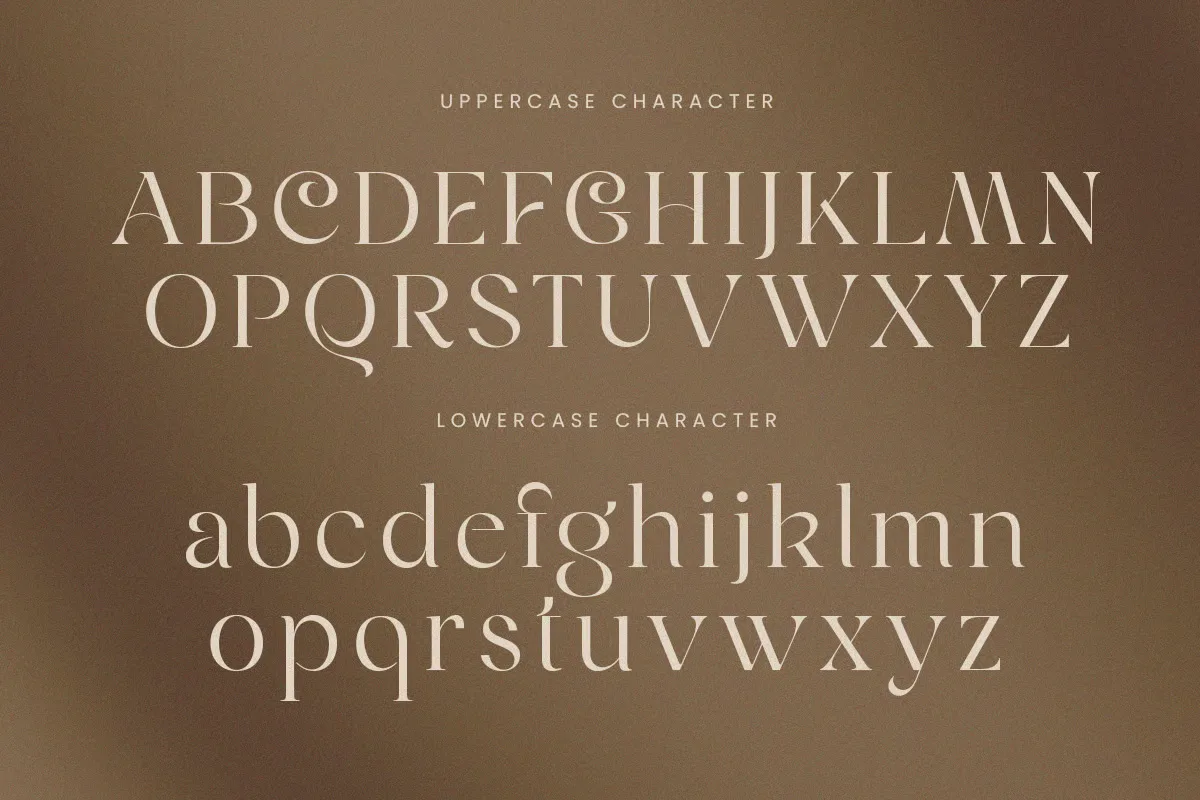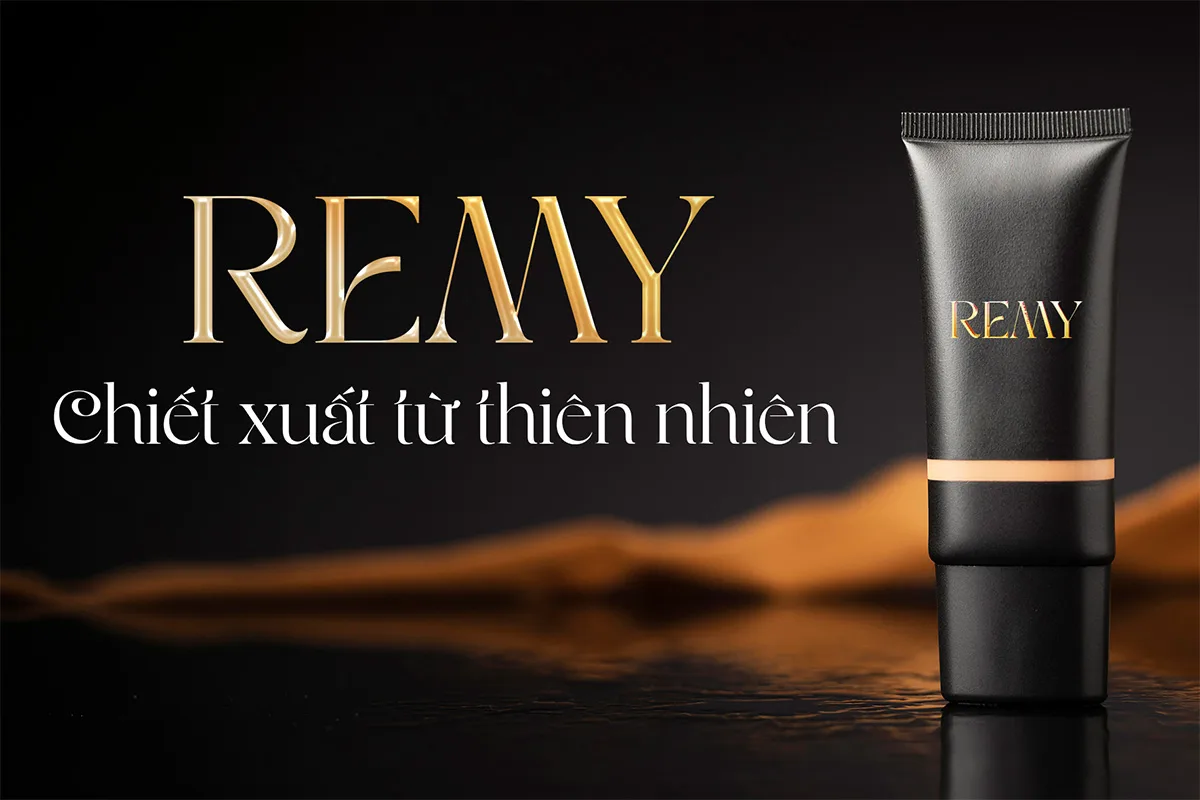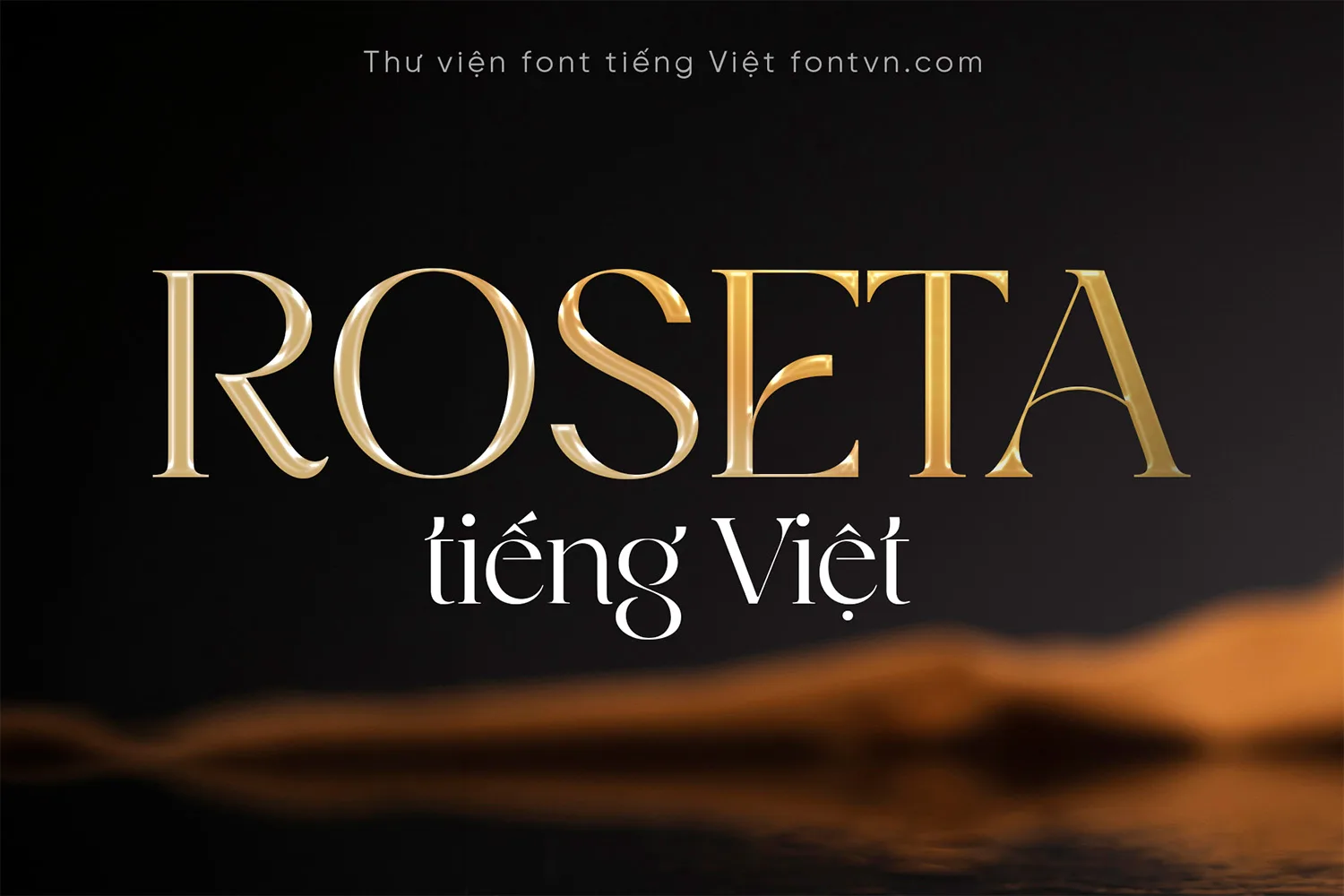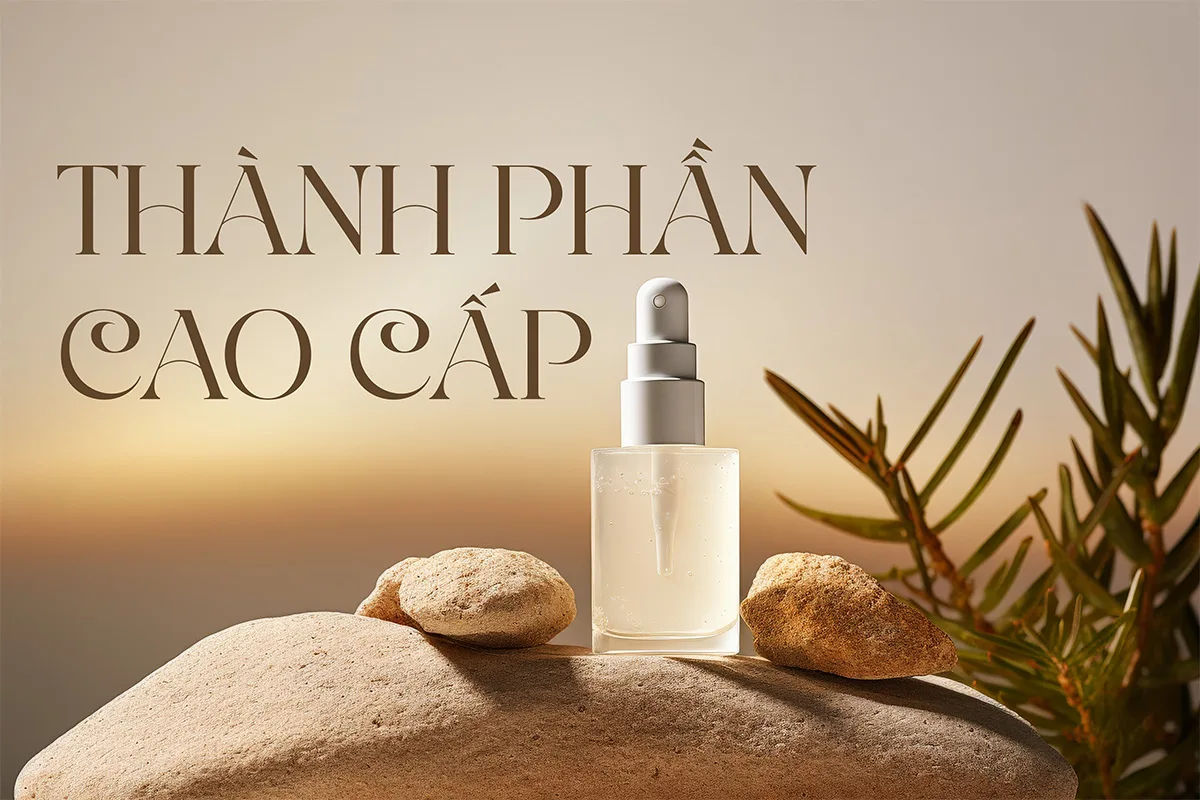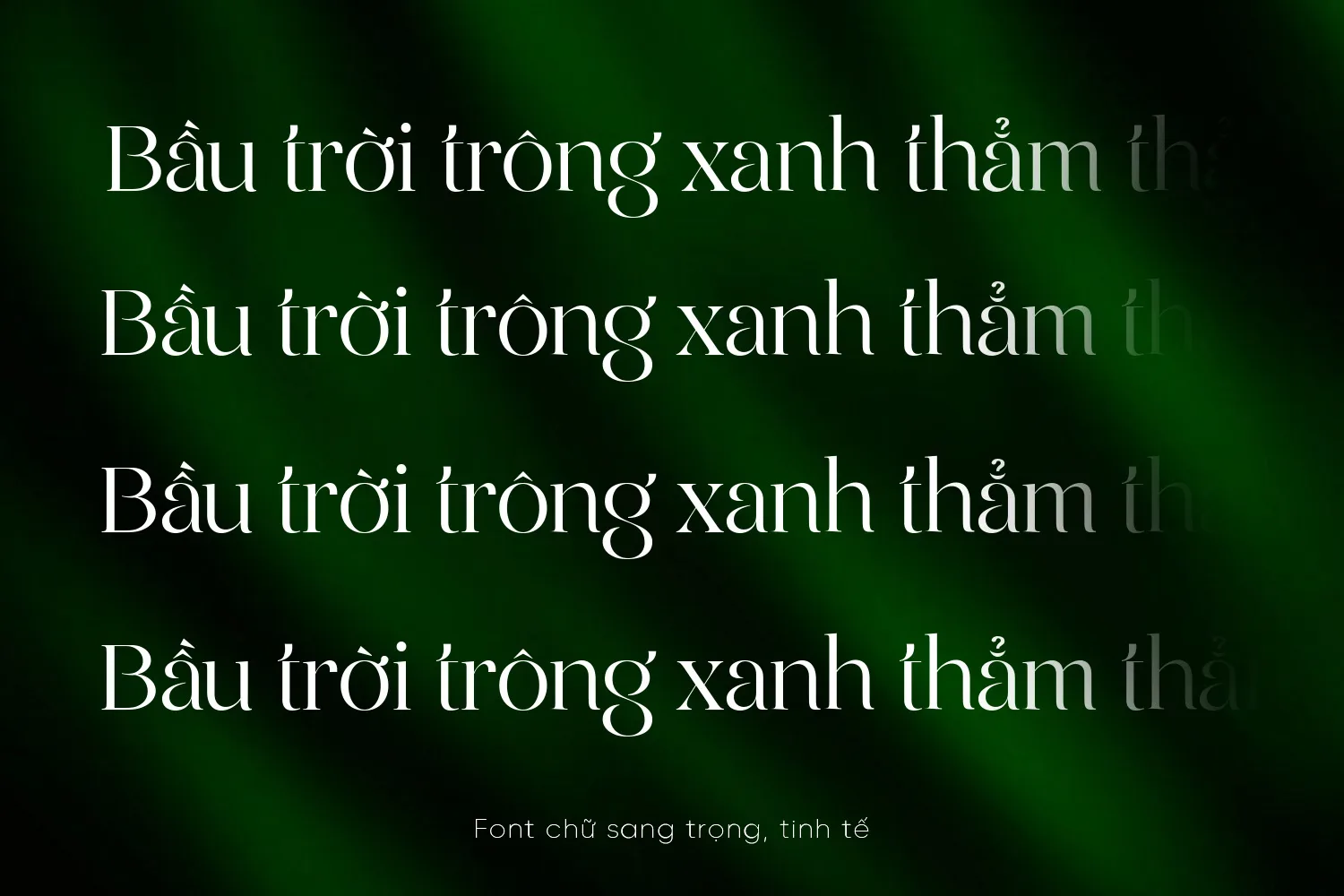
DVN Roseta tiếng Việt – Font chữ Serif Sang Trọng Và Quý Phái
DVN Roseta mang đậm ngôn ngữ thiết kế của một dòng serif cổ điển kết hợp tinh tế với hơi thở nghệ thuật đương đại. Điểm nhấn thị giác của kiểu chữ này nằm ở độ tương phản thanh đậm tinh tế, đi kèm với các chi tiết uốn lượn (swash) điệu đà được xử lý khéo léo trên những ký tự đặc thù. Sự giao thoa hài hòa giữa cấu trúc serif vững chãi và các đường cong uyển chuyển giúp tổng thể DVN Roseta không chỉ toát lên vẻ đẹp quyến rũ, thanh lịch mà còn giữ được sự sắc sảo, quý phái trong từng nét chữ.
Với diện mạo mang đậm tính nghệ thuật và sự sang trọng, DVN Roseta là giải pháp định hình phong cách hoàn hảo cho các ấn phẩm đòi hỏi tính thẩm mỹ cao. Kiểu chữ này đặc biệt phát huy thế mạnh khi được ứng dụng vào thiết kế nhận diện thương hiệu cao cấp, tiêu đề tạp chí thời trang, thiết kế bao bì mỹ phẩm xa xỉ hay những bộ thiệp cưới mang phong cách lãng mạn. Dù xuất hiện ở các không gian thiết kế tối giản hay phức tạp, DVN Roseta đều tạo ra sức hút thị giác mạnh mẽ, giúp nâng tầm đẳng cấp và truyền tải trọn vẹn tinh thần của dự án.